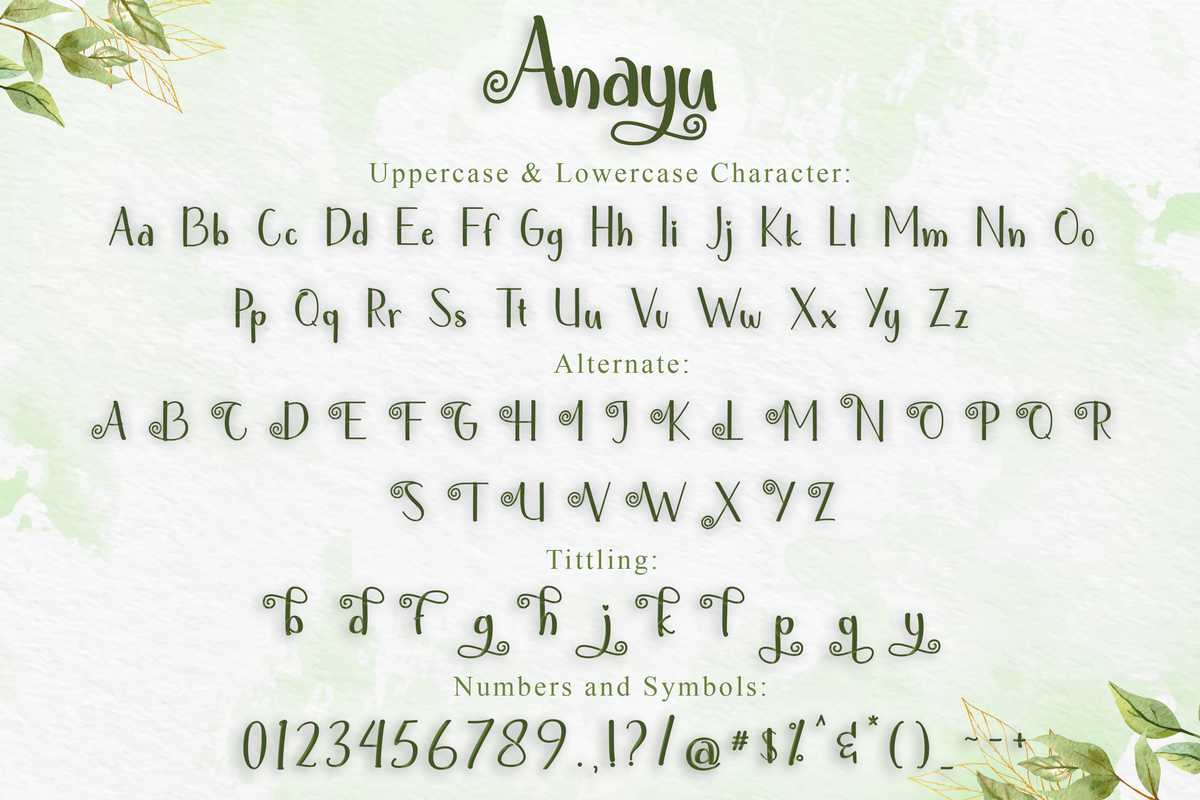
Anayu是现代和书面形式的MadebyrashatType。它选择适合任何设计的打印输出,如贺卡、模型、打印报价单和TC。只需尝试一下,我希望它会为您带来快乐。谢谢:)Anayu是现代和书面形式的MadebyrashatType。它选择适合任何设计的打印输出,如贺卡、模型、打印报价单、,并希望它能为你带来快乐。谢谢:)